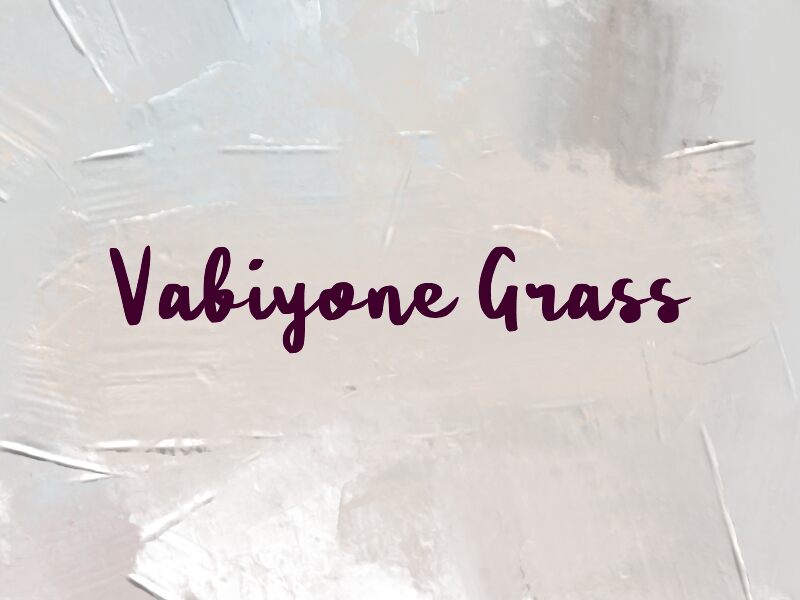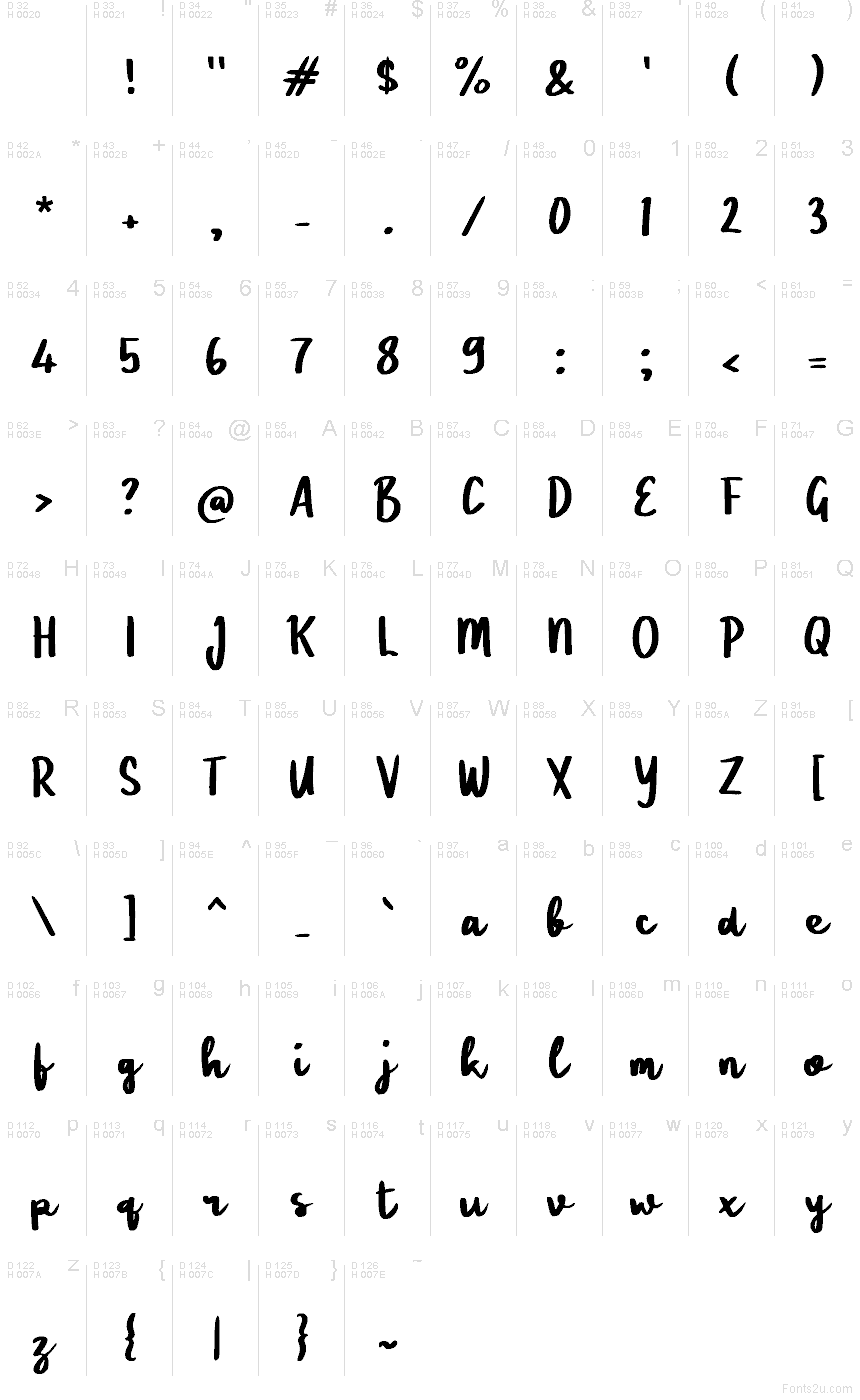
Vabiyone Grass
Vabiyone Grass di Wep è un font script a pennello gratuito che cattura la naturalezza della scrittura veloce da insegna. Le lettere si muovono con tratti spessi e carichi di inchiostro, alternando giunzioni morbide e arrotondate a occhielli alti e lunghe code discendenti, dando al carattere un aspetto spontaneo e non troppo rifinito.
Si adatta perfettamente al branding di caffè e linee beauty, packaging rilassati, titoli di poster, post sui social media e copertine in cui un tocco umano e scritto a mano aiuta a rafforzare il messaggio. Essendo un font gratuito, funziona bene anche per brevi titoli o monogrammi, poiché le sue giunzioni ampie e le discendenti allungate conferiscono una silhouette vivace anche alle parole più brevi.